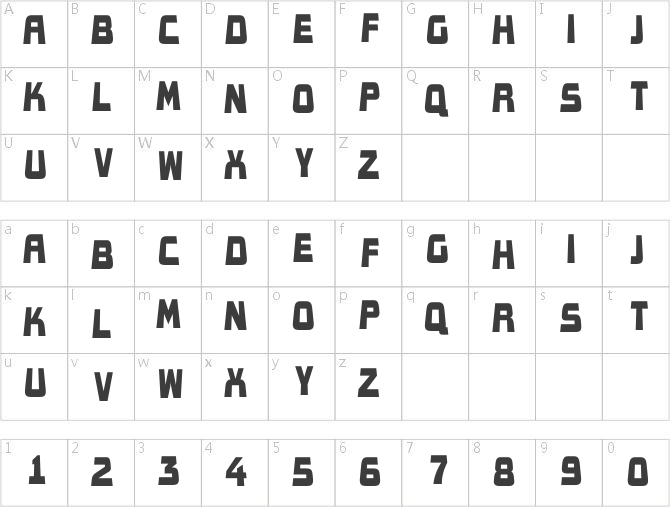
a_ConceptoTitulLdBk 詳情頁(yè)
a_ConceptoTitulLdBk字體字庫(kù)是一款讓人賞心悅目、百看不厭的英文字體,適合各類(lèi)廣告和產(chǎn)品包裝設(shè)計(jì)應(yīng)用,字體大小0.03MB,格式為ttf字體,上傳用戶是W^xzj,作者/版權(quán)方為未知